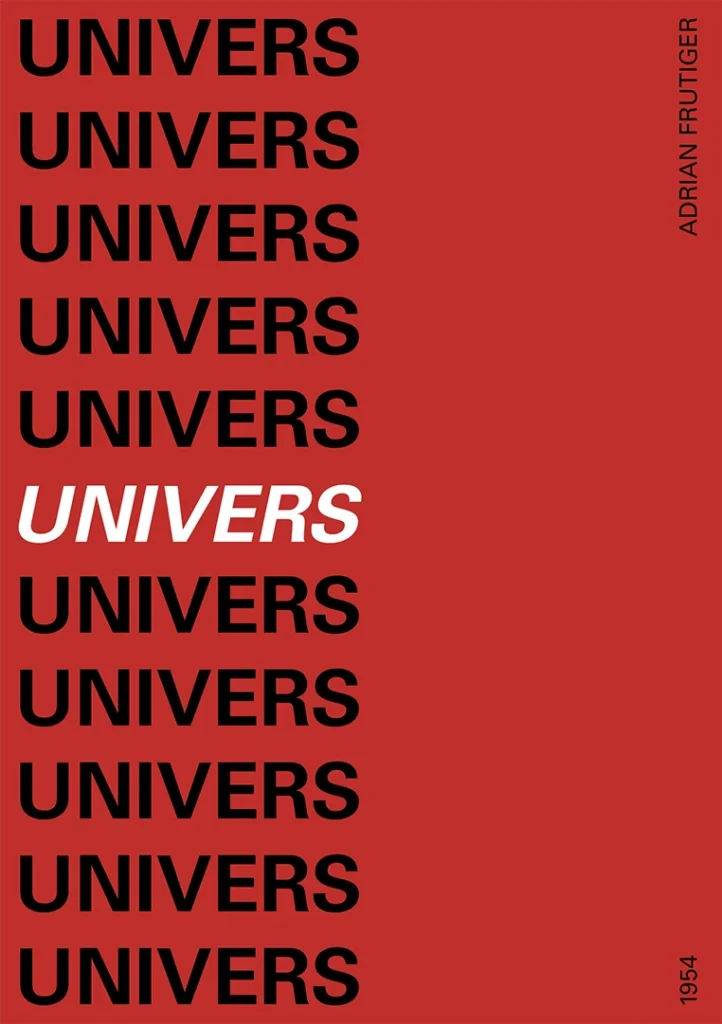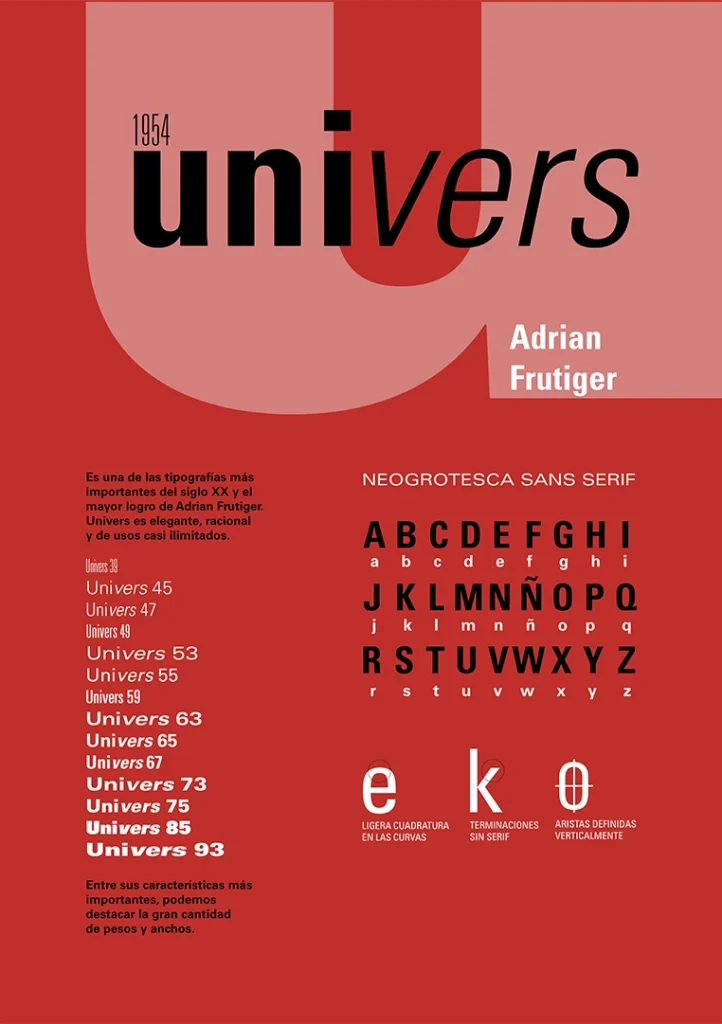
Es un tipo de letra sans serif neogrotesca diseñada por el tipógrafo suizo Adrian Frutiger en 1957.
Según Emil Ruder (1914-1970) «con la aparición de la Univers se satisfacía una demanda de la tipografía moderna que hasta aquel momento sólo había sido una pretensión teórica». El sistema completo de 21 variables que presentó este diseño era innovador y sumamente racional. Para evitar la ambigüedad de nombres como bold, demibold, etc se numeró a las distintas variantes en relación al número 55 fue asignado al peso regular. «Es el centro de una cuadrícula: debajo están los pesos en negrita y arriba los ligeros. Hice un pequeño ejercicio decimal», afirmaba Frutiger.